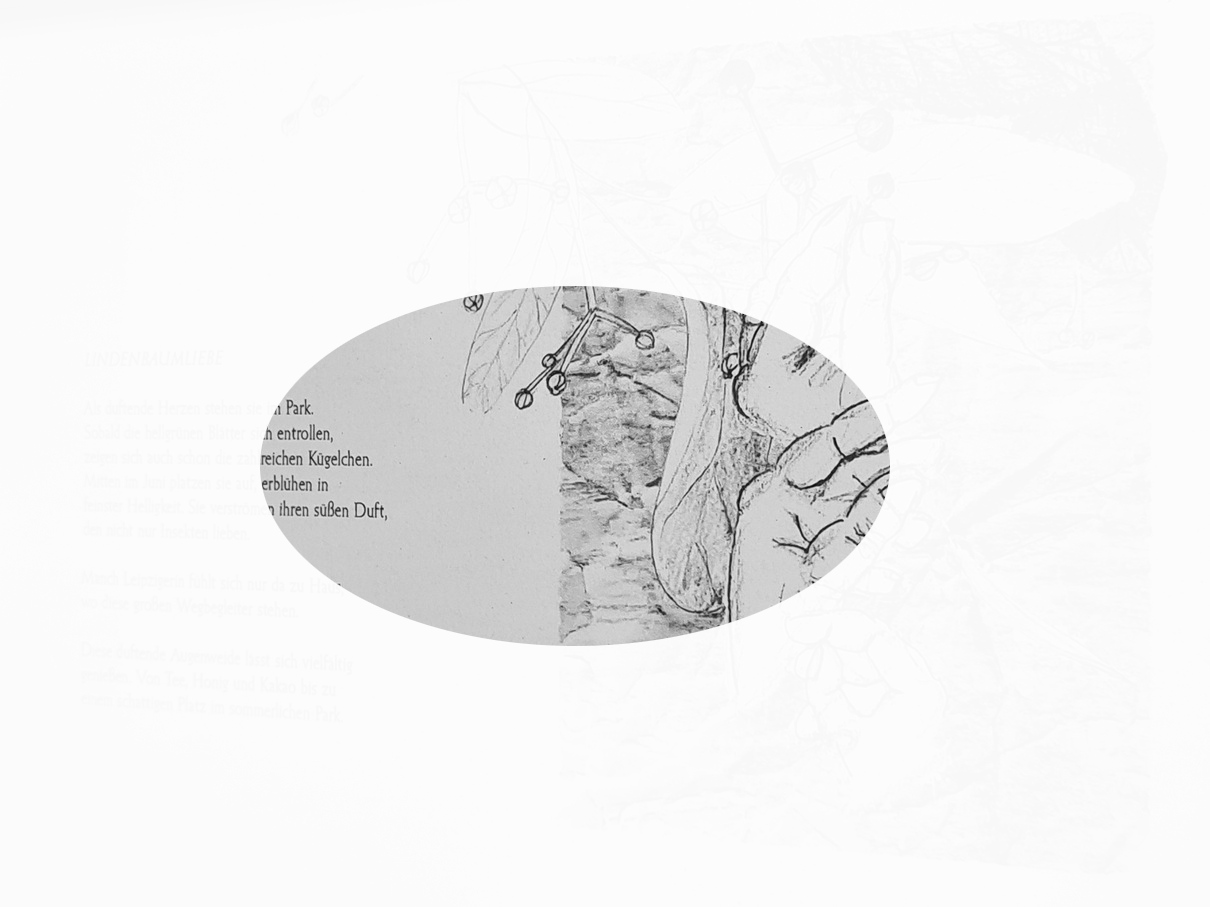
Vorschau auf Zeichnung und Text von Annett Riechert.
Buchkalender für 2027: Begegnungen am Wegesrand – ein Projekt der B.a.c.H. Frauen
Label: b.a.c.H.– book art center Halle.
Beteiligte: Anett Hoffmann, Ilkay Unay-Gailhard, Ondine Frochaux, Odine Lang, Lisa Rackwitz, Sara Möbius, Charlotte Ehrt, Petra Reichenbach, Annekathrin Pohle, Barbara Dimanski, Luzia Werner und Annett Riechert.
Schriften: FreightSans Pro, Moon Phases und Elizabeth. Letztere Schrift wurde zur Erinnerung an die Schriftgestalterin Elisabeth Friedländer (1903 – 1984) ausgewählt. Entworfen wurde die Schrift als Friedländer, aufgrund des jüdischen Namens wurde die Schrift noch im Jahr der Veröffentlichung 1933 in Elisabeth umbenannt.